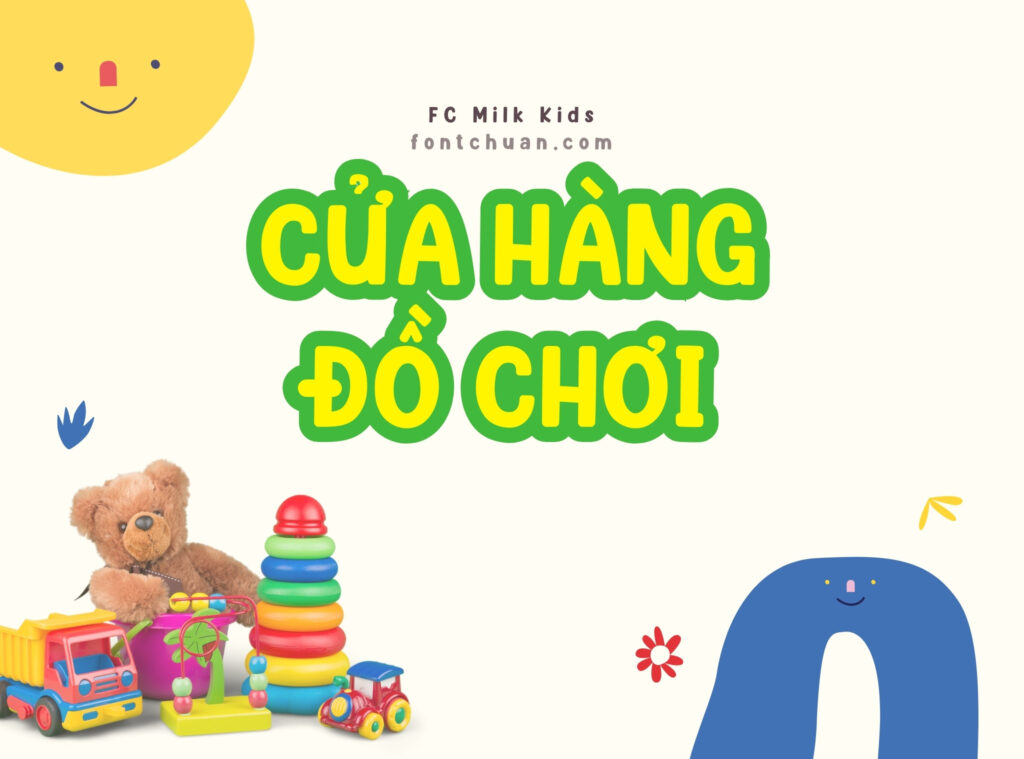
Font “Milk Kids” là một kiểu chữ hiển thị vui nhộn và thân thiện, được thiết kế bởi Manjali Studio. Với các đường nét tròn trịa và đậm nét, font này mang lại cảm giác hồn nhiên, đáng yêu và có thể trở thành một Font Lễ hội sinh động cho các ấn phẩm sự kiện, thiệp mừng hoặc các dự án thiết kế vui tươi. Đồng thời, “Milk Kids” cũng có thể được sử dụng như font ngày nhà giáo Việt Nam, tạo điểm nhấn tươi sáng, thân thiện cho các thiệp mừng, poster và banner chúc mừng thầy cô. Font này hỗ trợ đa ngôn ngữ, bao gồm tiếng Anh, Java, Ý, Cebuano, Malagasy, Swahili, Filipino, Afrikaans, Catalan, Pháp, Đức, Bồ Đào Nha, Thụy Điển và Tây Ban Nha.
Về đặc điểm thiết kế, FC Milk Kids Việt Hóa sở hữu các ký tự đậm, tròn trịa và đồng nhất, tạo nên sự dễ đọc và thu hút cho người xem. Font này phù hợp cho nhiều ứng dụng như thiết kế các ấn phẩm liên quan đến trẻ em, sách thiếu nhi, trường học… ngoài ra còn ứng dụng cho tiêu đề, logo và các ấn phẩm truyền thông khác. Các ngành nghề như quảng cáo, giáo dục, ẩm thực và spa có thể tận dụng “FC Milk Kids” để tạo ra những sản phẩm ấn tượng và chuyên nghiệp.